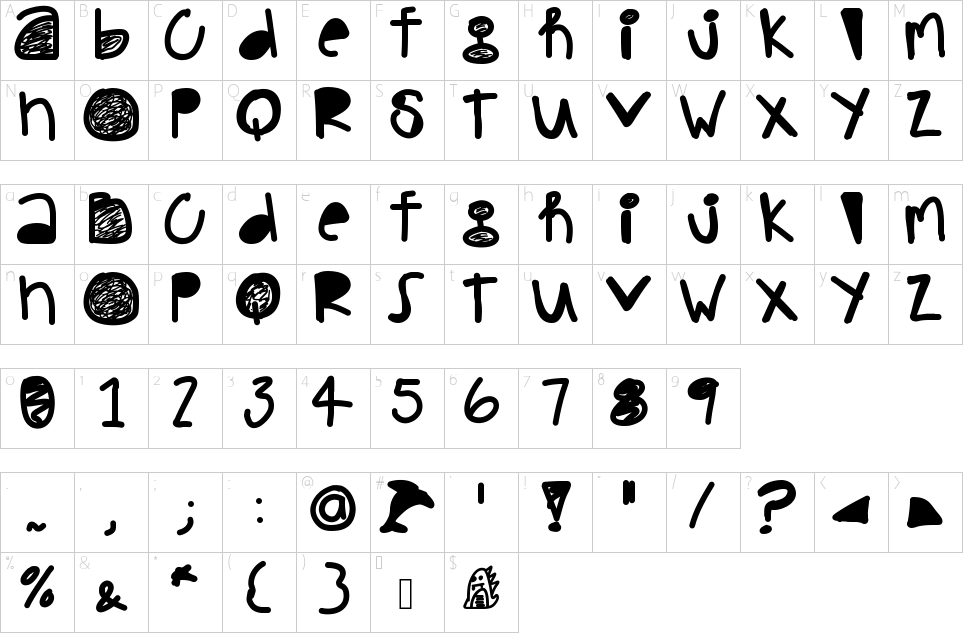
A Pink Dolphin Font é uma fonte gráfica linda e colorida para Windows e Mac, criada por Des Gomez. Embalada com um toque de diversão e criatividade, esta fonte adora ser usada em sites, blogs e até mesmo em documentos pessoais. Desenvolvida para dar vida aos seus projetos, ela traz uma mistura única de elegância e brilho, perfeita para aqueles que buscam uma fonte especial que dê vida a qualquer trabalho. Com uma baixa de 1,848 downloads, o Pink Dolphin Font já está provando ser um dos recursos indispensáveis para qualquer criador de conteúdo.